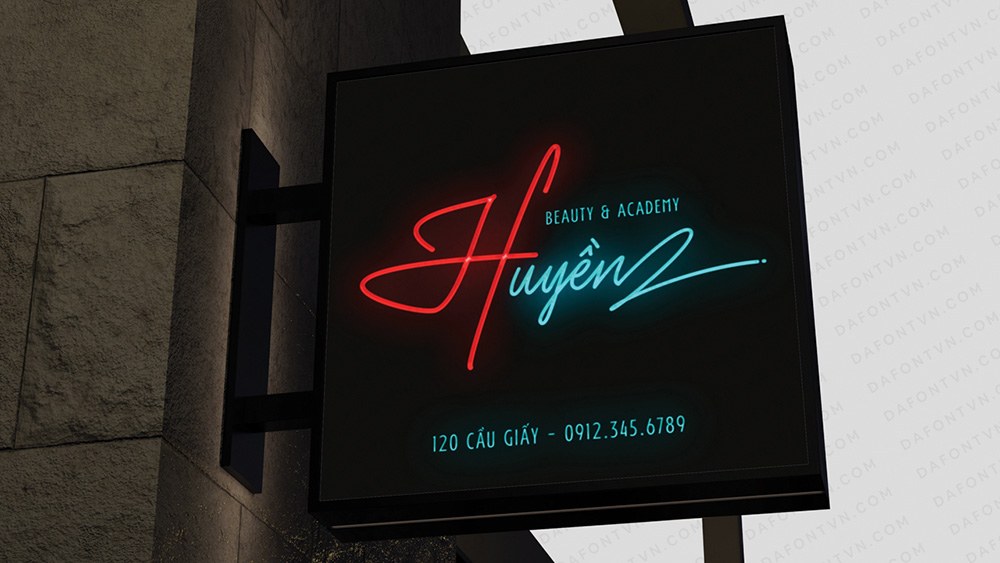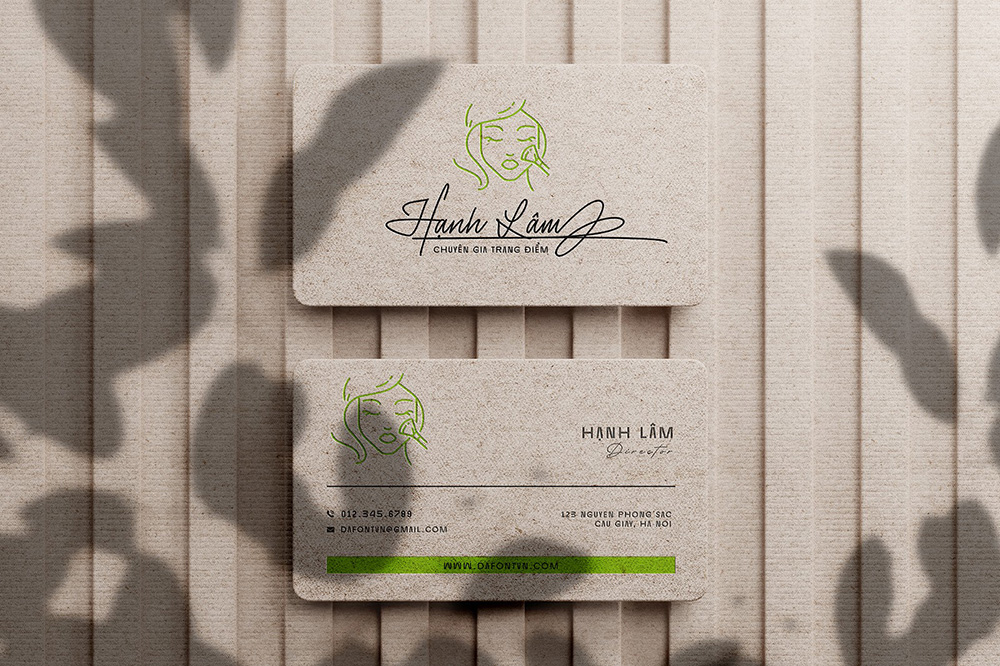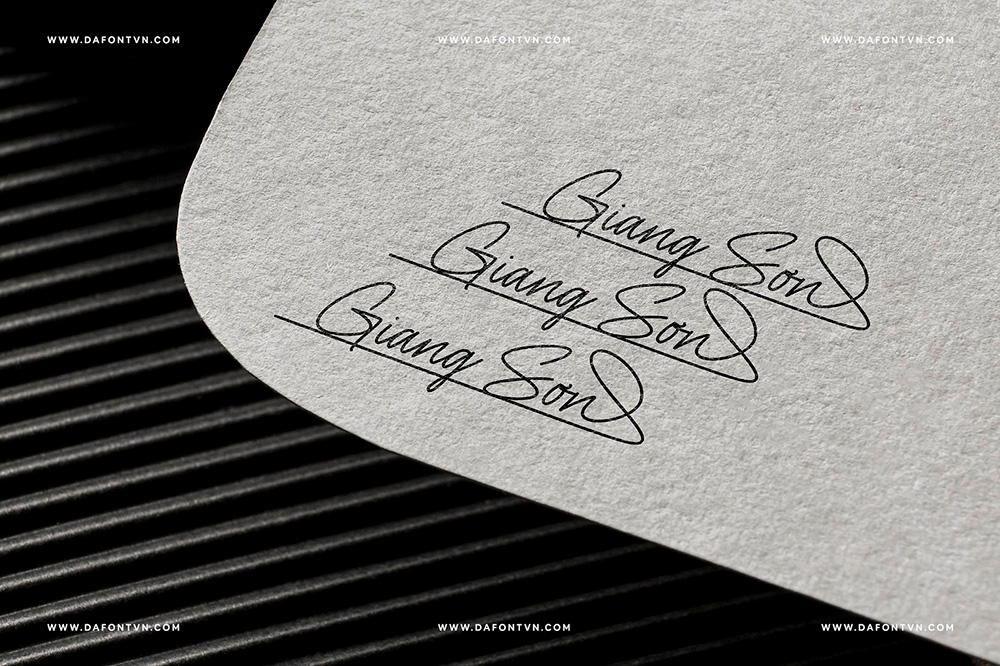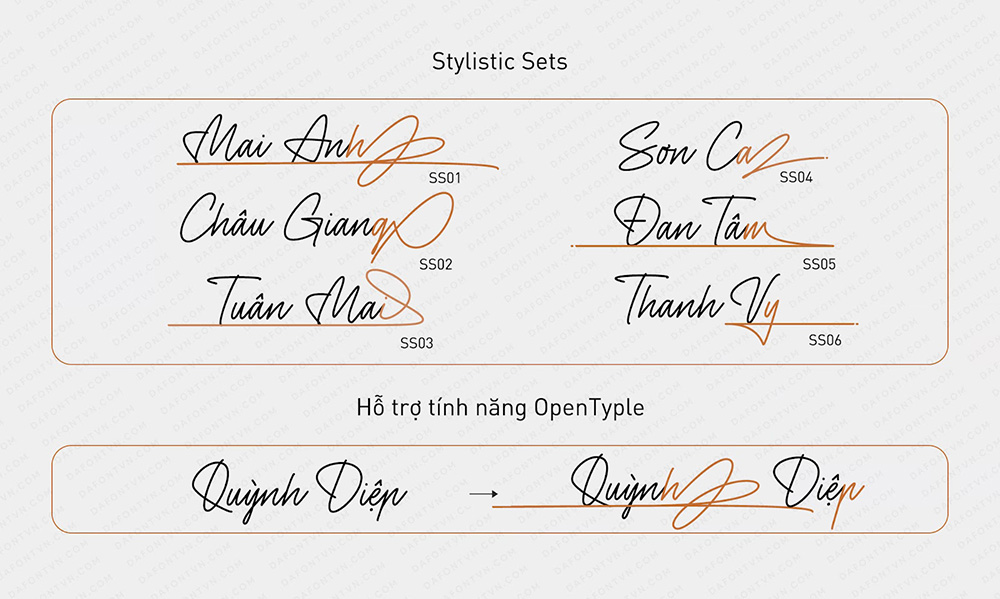
Font Việt Hóa - Sarion Mang Phong Cách Mềm Mại, Thanh Lịch
Sarion là một font chữ ký đẹp mắt với phong cách monoline, mang đến sự mềm mại và thanh lịch.
Font chữ này có cảm giác gọn gàng và mượt mà, chắc chắn sẽ tạo nên điểm nhấn cho bất kỳ thiết kế nào mà bạn sử dụng. Nó hoàn hảo cho nhiều dự án khác nhau như logo, xây dựng thương hiệu, thiệp mời, chữ ký, nhãn mác, nhiếp ảnh, và nhiều hơn thế nữa!
Ngoài ra Sarion còn bao gồm hơn 200 ký tự thay thế đẹp mắt mang đến khả năng sáng tạo và kết hợp để dễ dàng tạo ra những thiết kế ấn tượng cho dự án của bạn.
Font Việt Hóa - Sarion Roman Mang Phong Cách Mềm Mại, Thanh Lịch